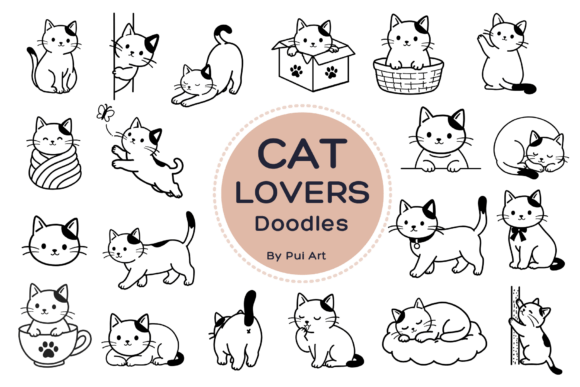
Cat Lovers Doodle
Att hitta rätt designelement kan vara utmanande, men Cat Lovers Doodle erbjuder en exceptionell samling som omedelbart lyfter ditt arbete.
Oavsett om du skapar POD-produkter (Print on Demand), bröllopsinbjudningar eller grafik för sociala medier, är Cat Lovers Doodle ett perfekt val.